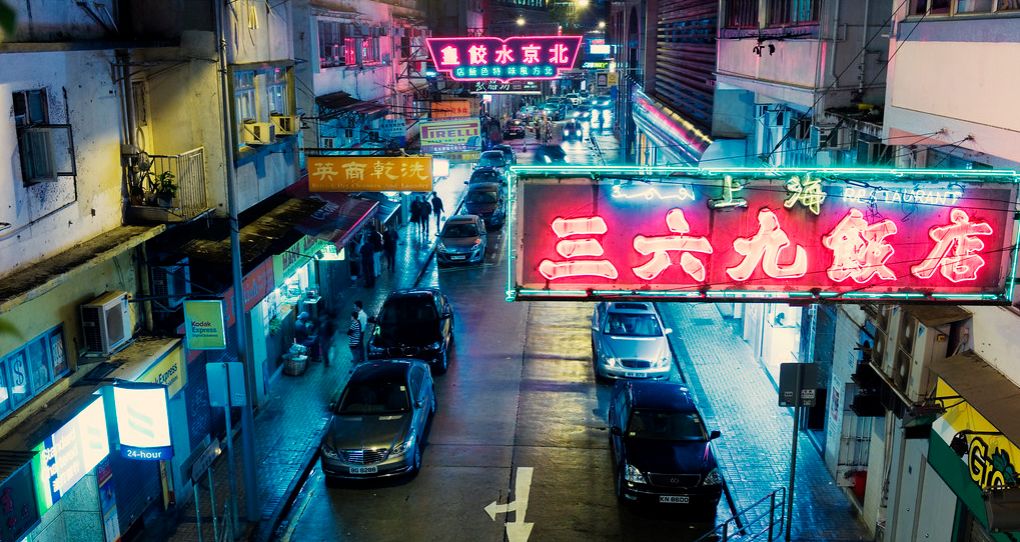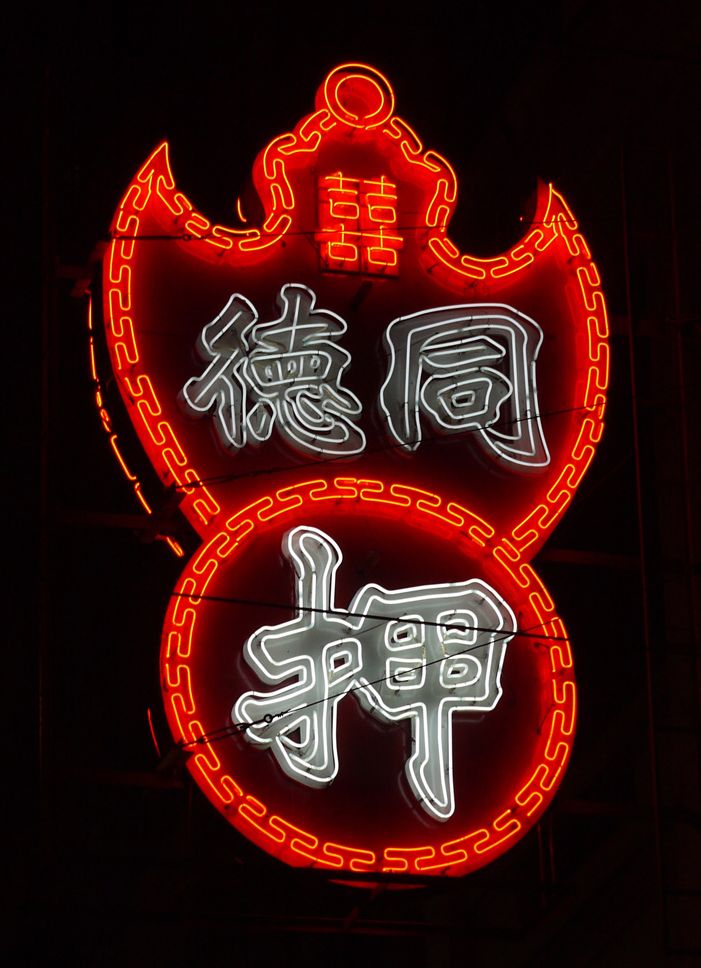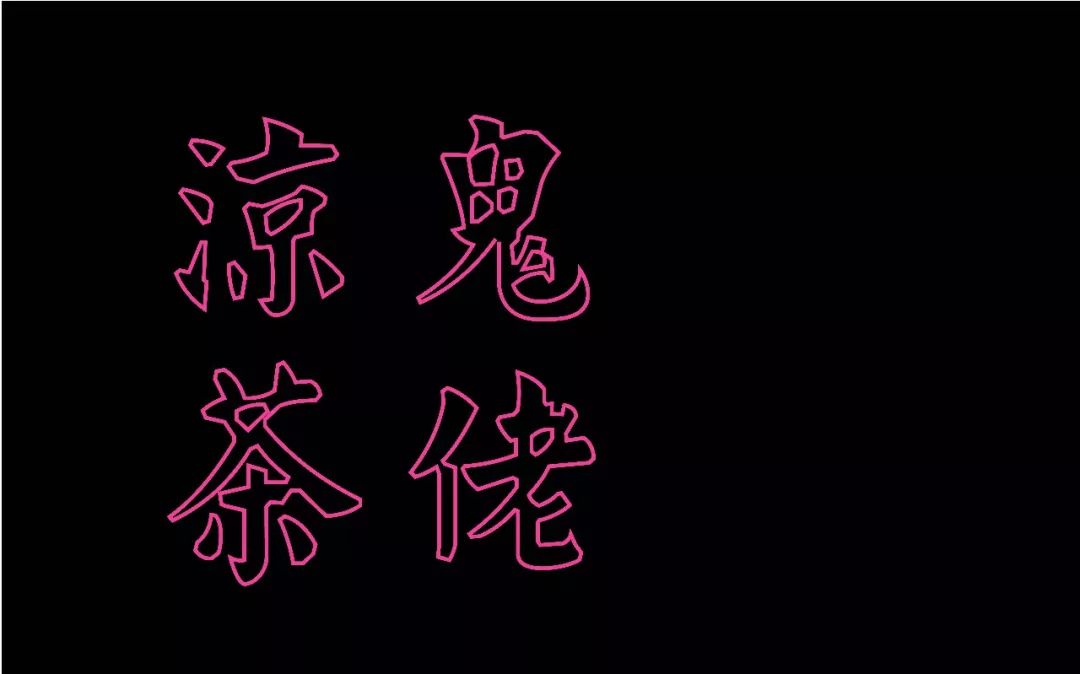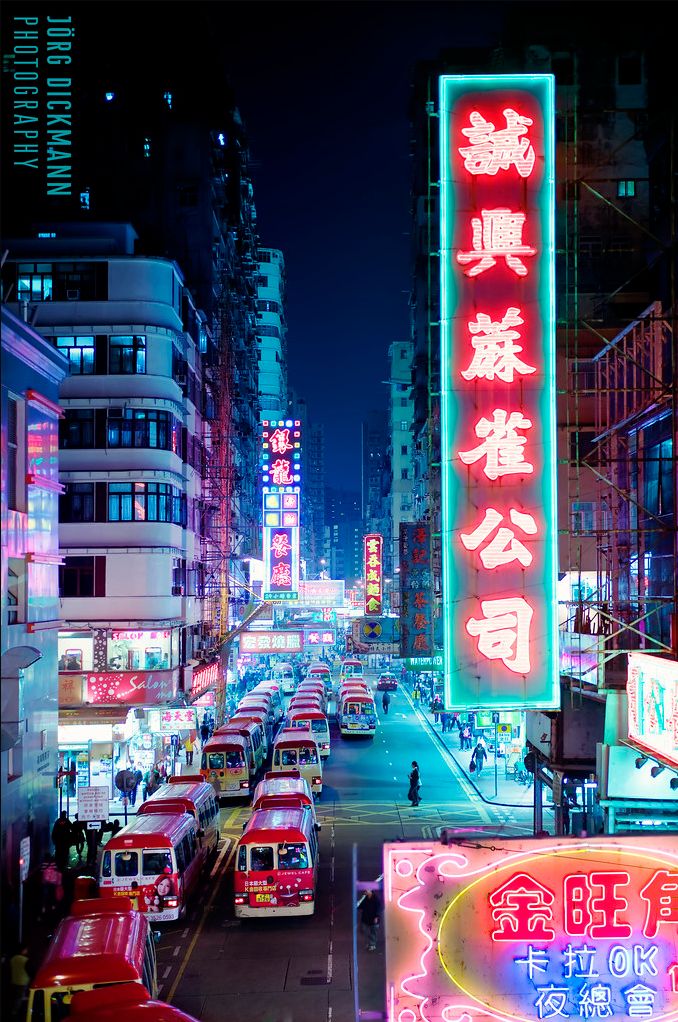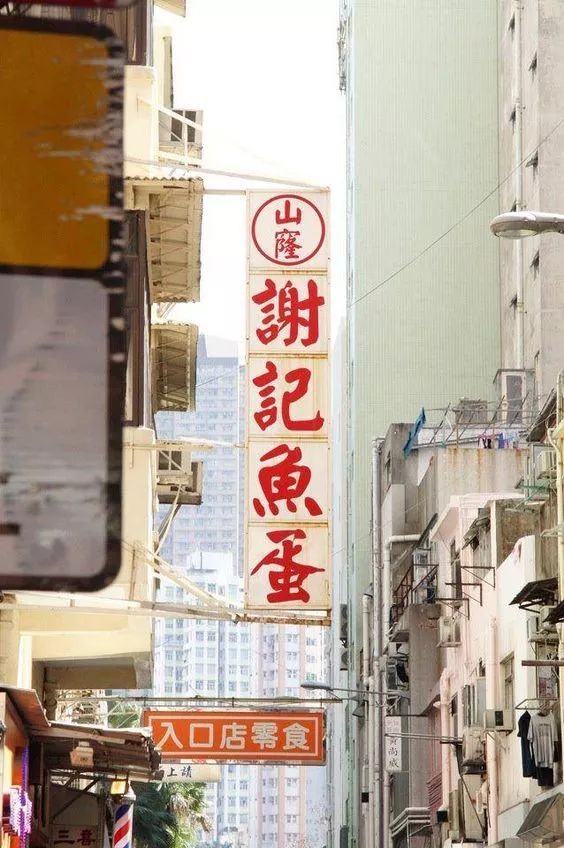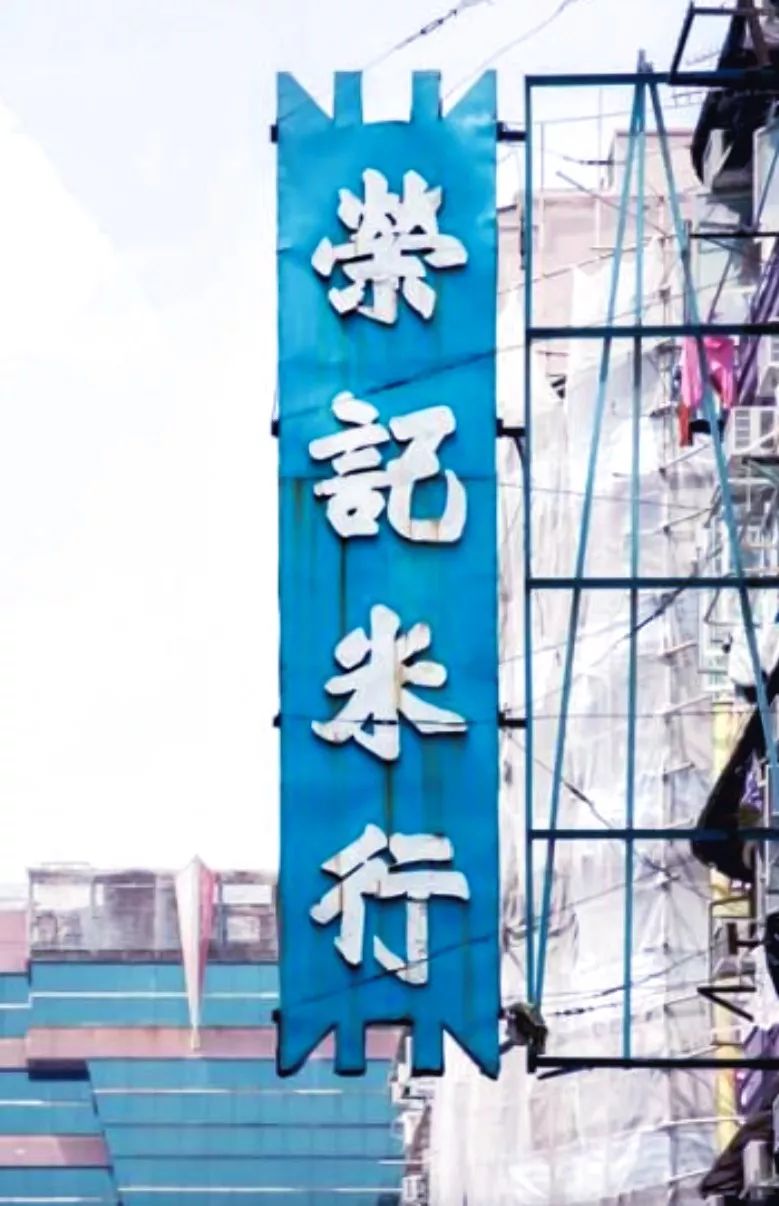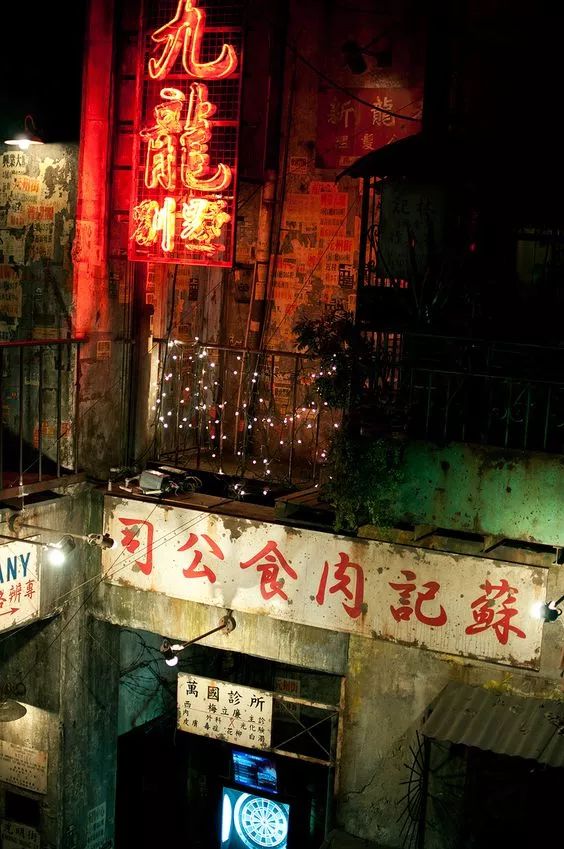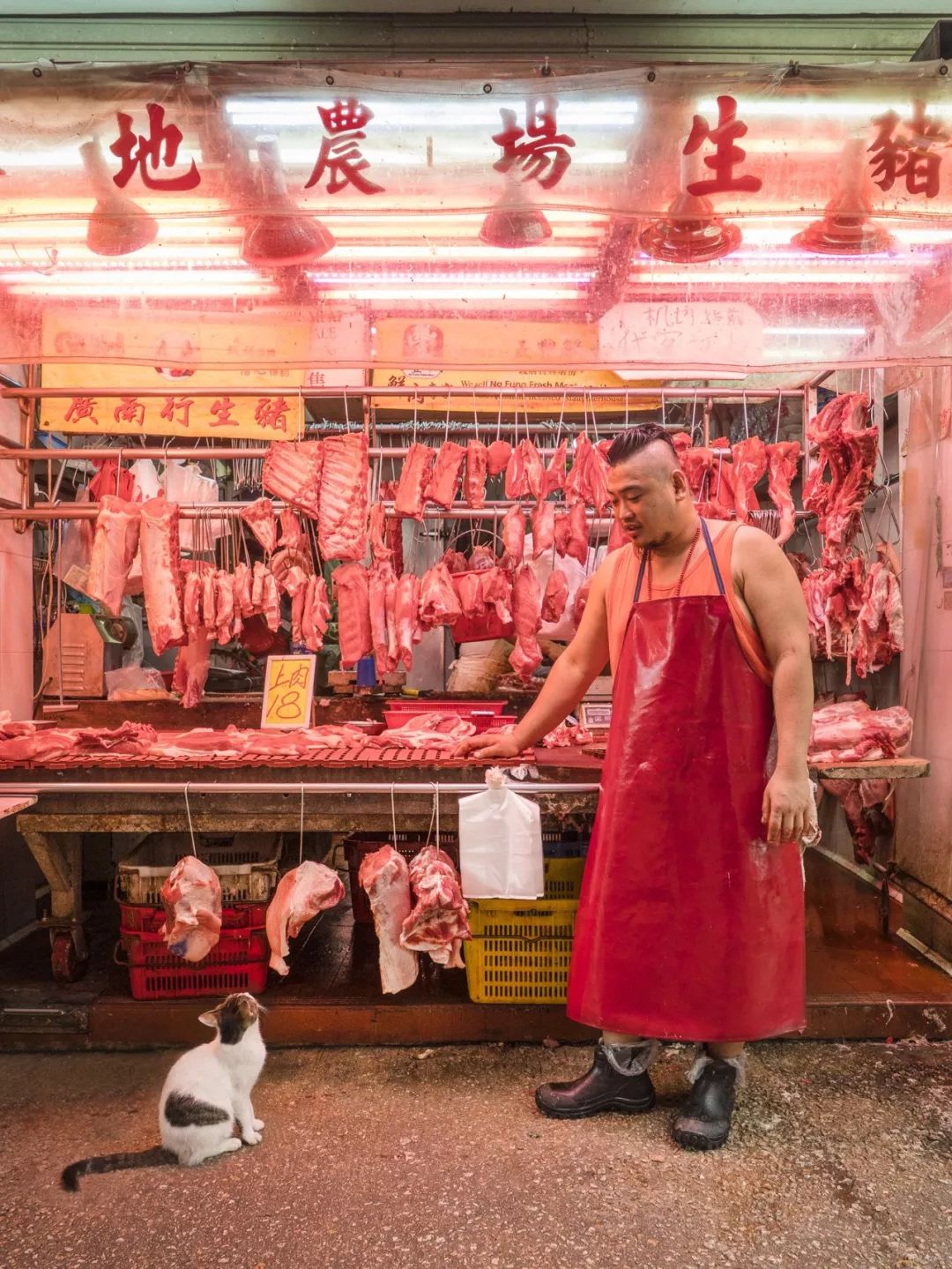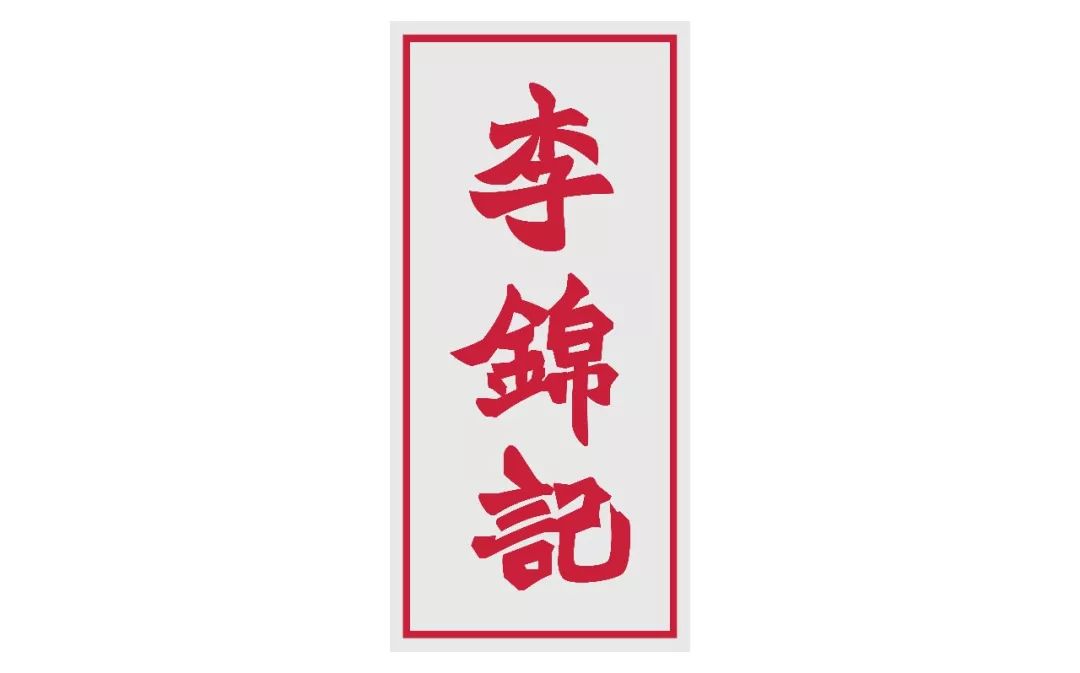
消逝的香港字体,流失的民族文化
大家好,我是小恺,平时喜欢字体设计,这次给大家分享关于香港招牌的字体设计。香港招牌使用的字体多且极具个性。在机打时代的今天,能给字体设计带来无限的可能性。
招牌的文化源远流长,深究起来其中人文色彩亦多浓郁,像同仁堂、全聚德、六必居等等京味老字号既有人文历史又有品质,称得上是当代传奇。
但是个例终究是个例,自从国内开始整治商铺“统一招牌”以后,制式带来的干净整洁,却也置审美需求于无地立足。即便历经时间摧残,其中也不乏能够展现美感的作品,比如香港便以错综复杂、霓虹闪烁的的街道招牌成为它的一张名片。
一提到香港给我印象最深的就是夜晚霓虹闪烁的招牌,霓虹招牌像一个视觉符号扎根于香港这座城市,成为了香港的缩影。
之后才慢慢了解到香港这种招牌林立、高低错落街道的招牌竟经历过数十年而不曾改变,这种“廉价”、“杂乱”的视觉效果竟然就是我们常说的港味本身。
到了夜晚,招牌上下缠绕的霓虹灯闪耀而起,回身而望街头,好像下一秒英伦风情的红色大巴车就要把我带向上个世纪的歌舞香港。
当时的香港招牌可以说是百家争鸣。各式各样的手写招牌应有尽有,北魏楷书、粗楷、隶书、榜书,遍布整个香港的大街小巷。
如果要找一款字体来代表香港招牌或者说是香港,则非北魏楷书莫属。香港的酒家、茶楼、五金行、同乡会,乃至大厦的名字里,都可以寻觅到北魏楷书的踪影。
说到北魏楷书就不得不提到一个人——区建公,广东新会人,一生致力文教工作,精书法,兼善各体,尤以北魏书体独步书坛。
电脑排版出现前,印刷字难以放大,各行各业的招牌得要找文人或字匠题字,于是店铺名外,会加「区建公题」之类,既收宣传之效,收费也会便宜一点。可见当时写字是一门生意,对书法家来说是一笔可观的收入。
五六十年代期间,区建公常以北魏书体书写招牌,深受大众喜爱。后来他开始开班授课,很多都会书写这种笔画厚重,着重字形结构的字体,这也为后来这种手书体在招牌上的普及和流行打下了基础。
北魏体能够在当时风行,主要因素是实用。招牌最重要是笔画要够粗和厚,吸引眼球,因此北魏最为适合。
北魏体结合碑帖的优点,令字型呈梯形或三角形,可以更稳重地悬挂于招牌上。北魏体看上去很精神、挺拔,从远处也能清晰可见。区建公的书法有力,起笔、收笔以及转折处的夸张,令字形容易辨认且极具风格。
以“李锦记”为例可以看到“记”字第三横横画比较长,目的就是取得平衡,令字体更有力度和容易识别。此外倔强有力的竖弯钩也使得整个字体极具个性和识别性。
例如夏字「夂」部的撇捺延伸夸张,呈三角形结构使整个字体非常稳健。
北魏体最容易识别的一个特征就是竖钩。竖划外线的弧度充满弹性,加上特别长的钩令整个字雄浑奇崛。
撇运用隶属的收笔重的特点,呈雁尾形。横折则多侧锋用笔。
但是继区建公之后,香港书法圈写北魏体的人也在逐渐减少。区建公除了招牌之外传世的作品很少。
那个时代的香港经济并不发达,加上英国殖民管治,公共事业尚未十分发达,大多是民间的商业活动较多,因此以书法谋生的他多写招牌而很少见到他其他的书法作品。
然而,随着店铺倒闭,旧楼拆迁区氏招牌也没能继续流行下去。随后在手写招牌这块开始出现断层,随着电脑的普及以及社会风气和品味的转变,电脑字取代手写字已成必然之势。
老一辈的人觉得生意是一辈子的事情所以不惜花钱找人写招牌,而现在生活节奏快速,店铺的升级更新很常见,这样就让这些老手艺逐渐没落了。
随着时代的变更,招牌在功能及感观上都有发生了转变。以往行人都依赖招牌引路及寻觅城市中热点,现在只需埋首于四寸宽的手机屏幕。
未来招牌或许更需要去权衡视觉和功能。沿着现在所谓的统一走下去,还是在老旧的招牌基础上进行整改让它们能有序的排列,这是一个值得深思的问题。我更希望能够将中国文化融入招牌之中,做出自己的味道。让街道重回昔日的,那种热闹喧嚣、充满烟火味道的感觉,愿每块招牌,都蕴含着人情的味道。